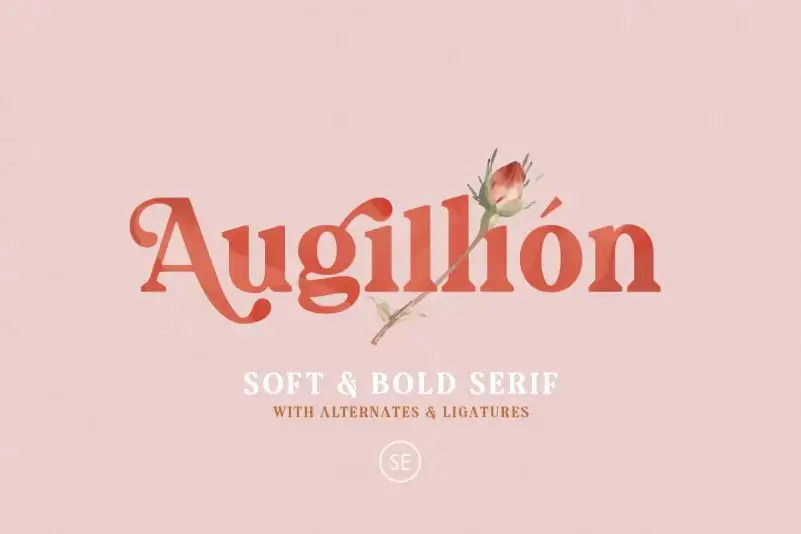
A Augillion Serif é uma fonte serif elegante que se destaca por sua limpeza e precisão, criando um visual moderno e atraente. O design combina elementos serif com swashes deslumbrantes, resultando num estilo único e sofisticado. Essa fonte adiciona um toque de originalidade às suas apresentações ou logomarcas, elevando-a acima do convencional para se destacar em qualquer cenário. O designer da font é o site 99designs, que oferece uma variedade de opções criativas e únicas. A Augillion ainda vem com suporte para múltiplas línguas e já está pré-carregada com codificação PUA (Propriedades Unicode Avançadas). Um detalhe especial é o caracter “✦”, que pode ser acessado simplesmente digitando A+ na interface de texto. Essa fonte não só complementará seu estilo, mas também dará um toque único a seus projetos. Engane-se se pensar que é apenas uma fonte; com a Augillion, você ganha uma ferramenta poderosa para personalizar e destacar sua identidade visual em qualquer formato.